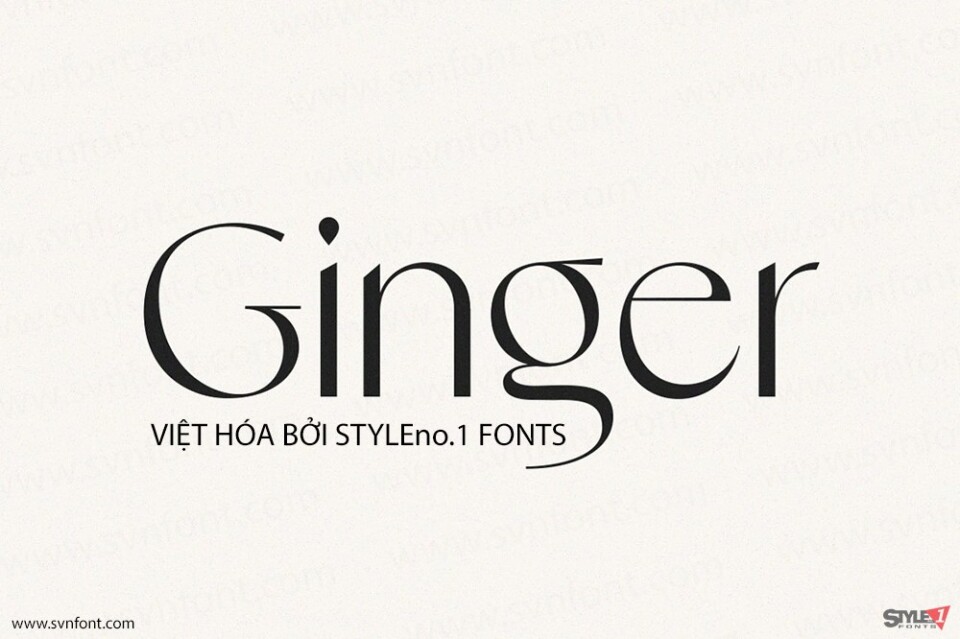
Font việt hóa SVN Ginger
Trong thế giới đồ họa hiện đại, việc lựa chọn Font Miễn Phí phù hợp đóng vai trò quyết định đến sự thành công của một tác phẩm. Font việt hóa SVN Ginger nổi lên như một lựa chọn hàng đầu cho các nhà thiết kế tìm kiếm sự kết hợp giữa nét cổ điển và tính ứng dụng cao. Đây là bộ phông chữ được tinh chỉnh kỹ lưỡng, hỗ trợ đầy đủ tiếng Việt, giúp người dùng không còn lo lắng về lỗi hiển thị khi soạn thảo văn bản hay làm tiêu đề sản phẩm.
Đặc điểm nổi bật của Font việt hóa SVN Ginger
Thiết kế thanh lịch và đa dạng
Bộ Font việt hóa SVN Ginger sở hữu những đường nét thanh mảnh nhưng vô cùng chắc chắn, mang đến cảm giác chuyên nghiệp và tinh tế. Với cấu trúc ký tự rõ ràng, phông chữ này cực kỳ phù hợp cho các bài thuyết trình tại trường học hoặc các dự án truyền thông sáng tạo. Khả năng đọc tốt của nó giúp học sinh và giáo viên dễ dàng truyền tải thông điệp một cách hiệu quả nhất.
Tính ứng dụng linh hoạt trong giáo dục
Không chỉ dùng trong in ấn, Font việt hóa SVN Ginger còn được ưa chuộng trong thiết kế bìa sách, poster sự kiện và trang trí báo tường. Sự linh hoạt này giúp các em học sinh thỏa sức sáng tạo mà không bị gò bó bởi các phông chữ hệ thống đơn điệu. Việc cài đặt cũng rất đơn giản, tương thích tốt với các phần mềm phổ biến như Word, Photoshop hay Canva.
Cách sử dụng và kết luận
Tối ưu hóa thiết kế với SVN Ginger